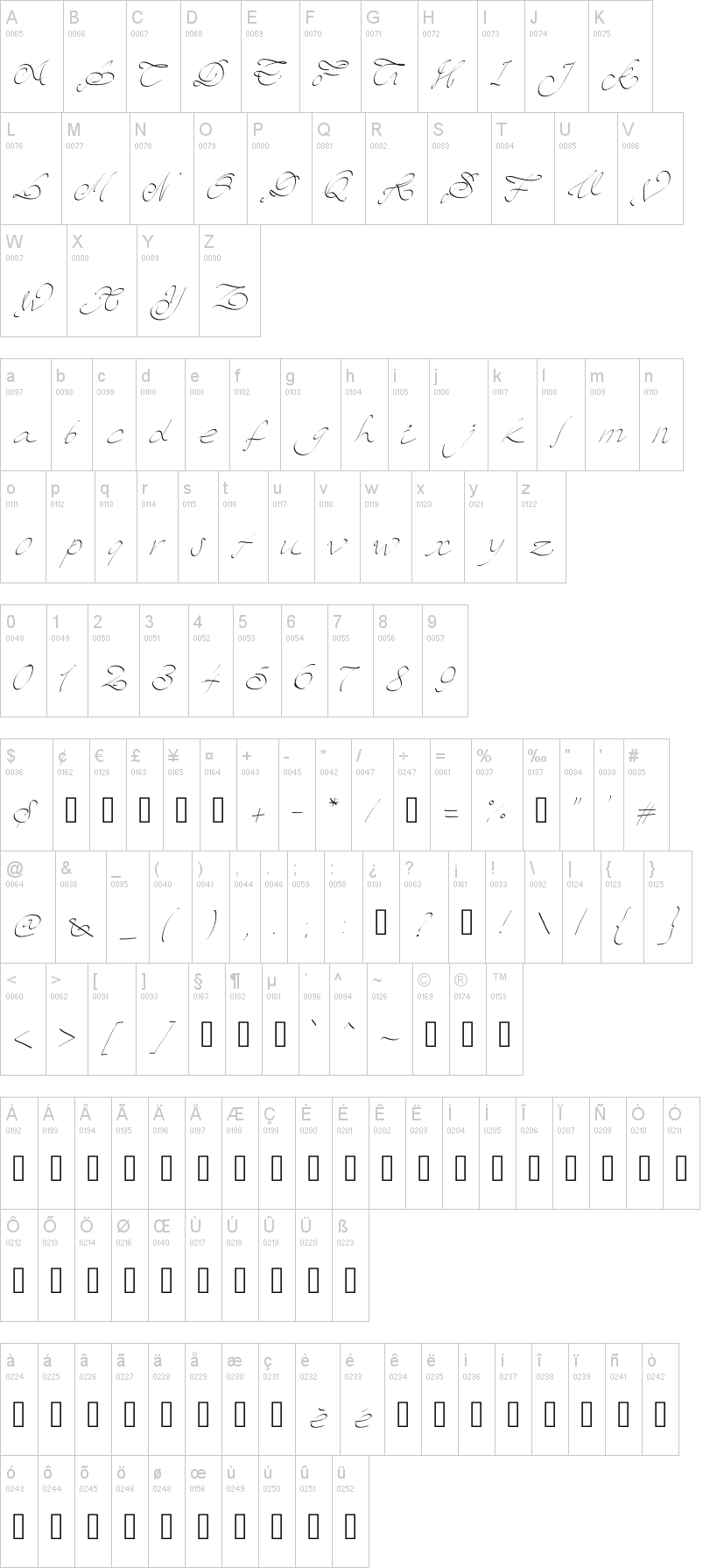
PW Script
PW Script 是一款经典的手写字体,由比利时设计师 Pierre Miedinger 创作。它是一款温柔而精致的字体,充满了欧式古典风格。它的字母形状优雅而有序,具有流畅的线条,使用它可以很好地表达出温柔、优雅的气质。PW Script 非常适合用于精致的设计中,比如婚礼邀请函、浪漫的封面、精美的贺卡等。
PW Script是一款非常不错的手写艺术字体,具有很好的视觉感,适合于文化类的宣传设计、商业类品牌的广告和产品包装设计以及个性化文字排版等较多场景。